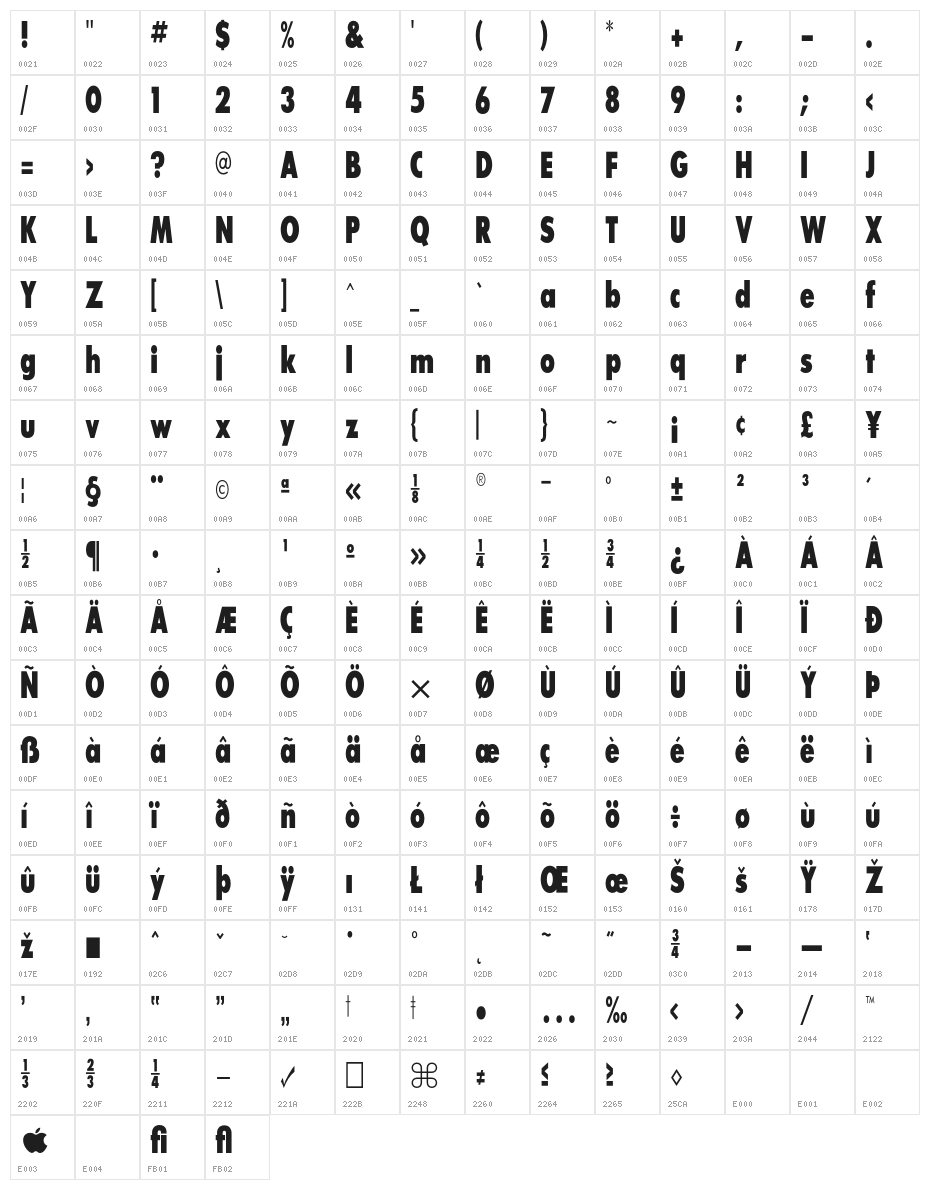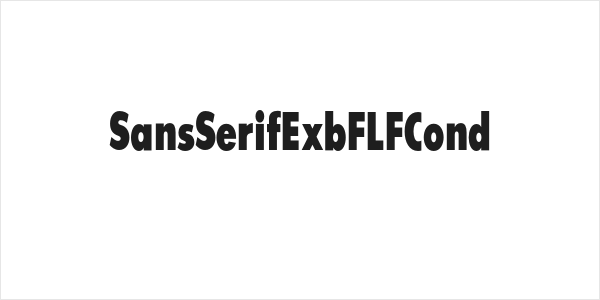
SansSerifExbFLFCond Font
| Vorgeschlagene Projekte | Ideal for branding, advertising, headlines, posters, and any project requiring a strong, modern typeface. |